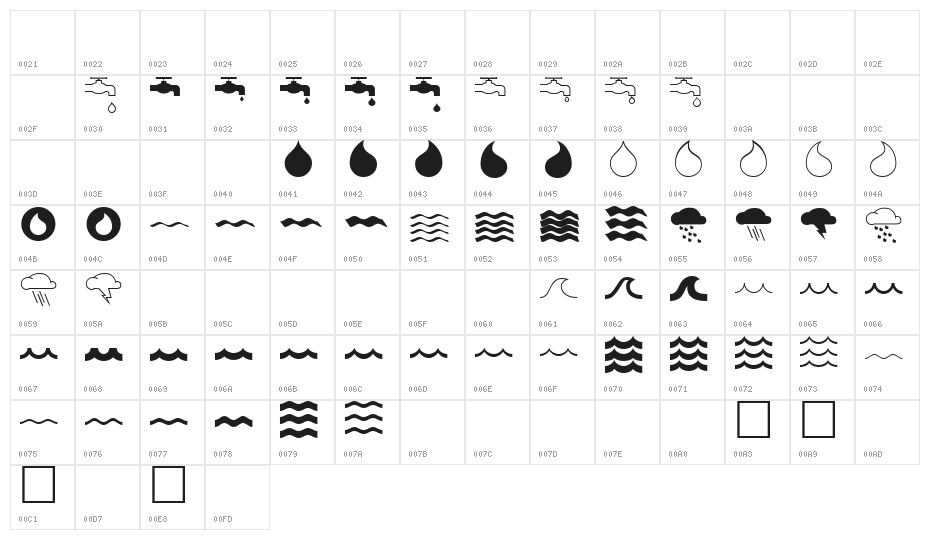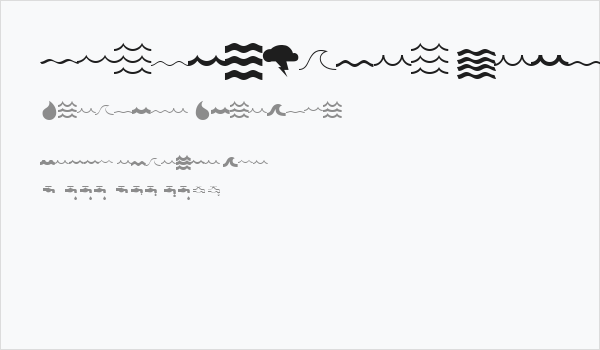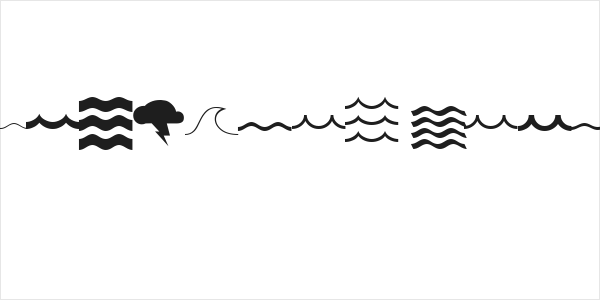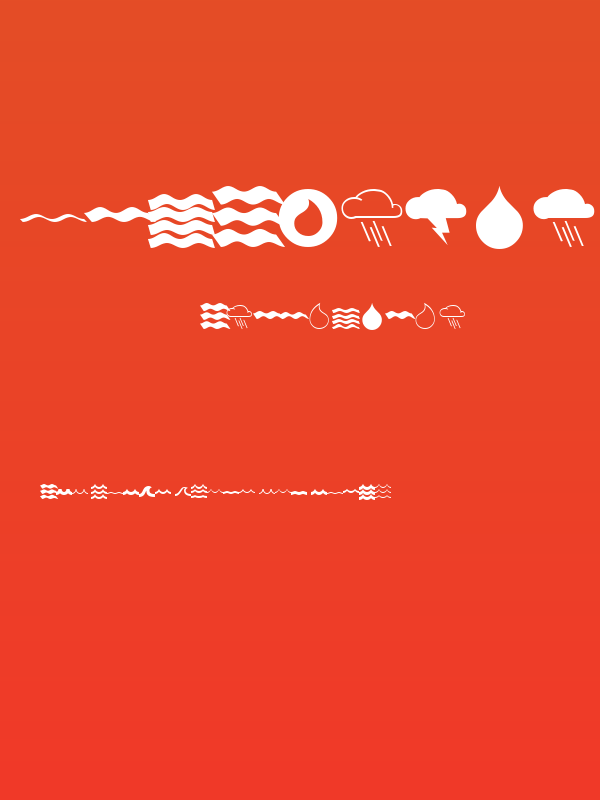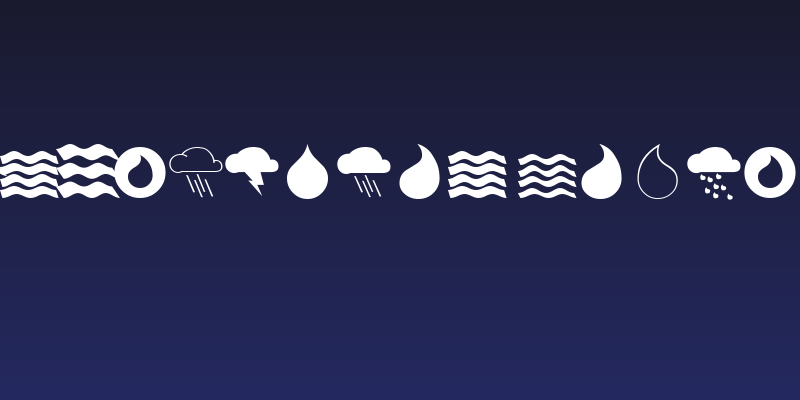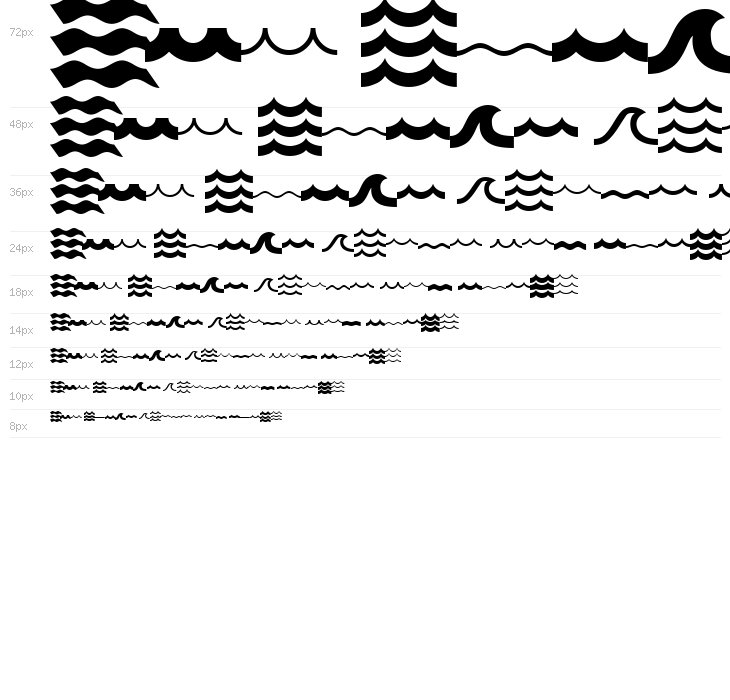
MostlyWaves Regular Font
| Caso d'uso | Logos, Posters, Educational Materials |
| Progetti proposti | Ideal for environmental campaigns, water conservation projects, educational materials on weather, and creative designs requiring thematic symbols. |